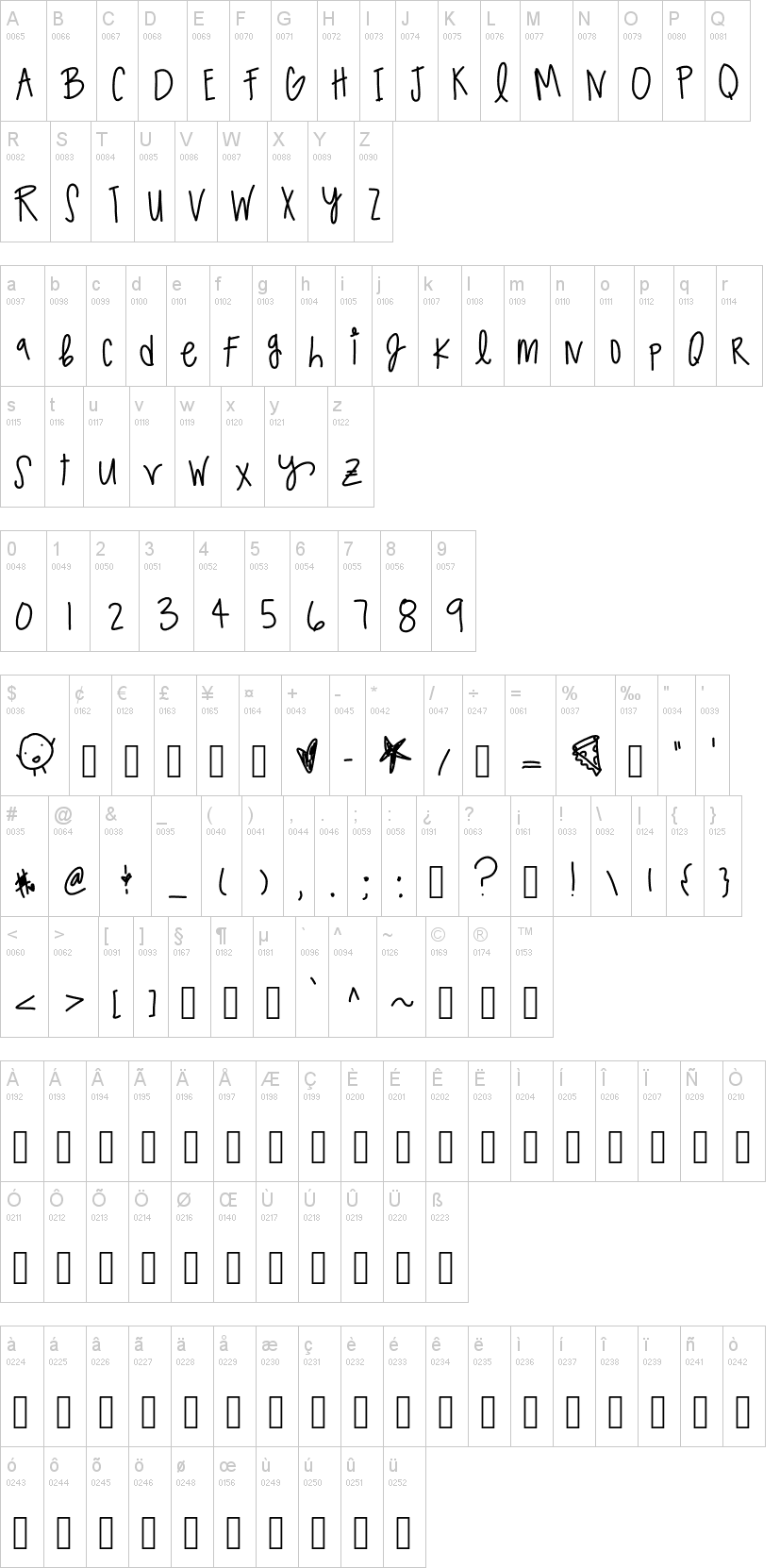
Sparkling Soda是一款漂亮而又充满活力的字体,它有一种甜美的气息,可以给你的设计带来活力和新鲜感。它的特点是圆润的笔画,温柔的轮廓,细节清晰,可以让你的设计看起来更加清晰,而且每个字母的曲线都有自己的特点,使你的设计更加丰富多彩。它可以用于报纸,杂志,海报,网站,印刷品等等,是一款非常适合用于创意设计的字体。内容介绍
Sparkling Soda是一款非常不错的手写艺术字体,具有很好的视觉感,适合于文化类的宣传设计、商业类品牌的广告和产品包装设计以及个性化文字排版等较多场景。